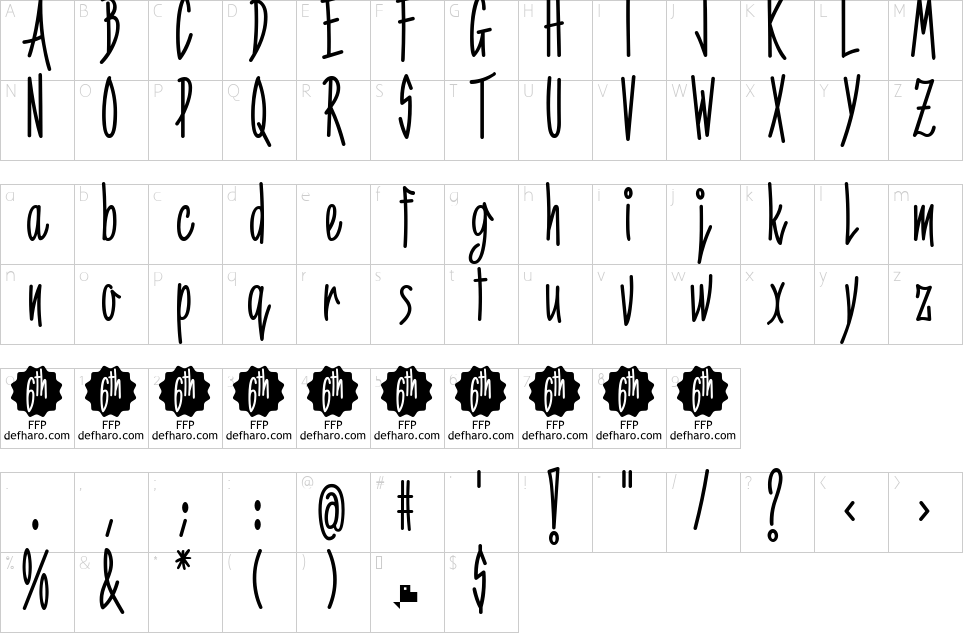
A fonte ‘6th Aniversario’ é uma criação estilosa que pode fazer um impacto significativo em seus projetos de design. Desenhada por deFharo, esta fonte foi desenvolvida com uma linguagem elegante e moderna, ideal para diversos estilos de design, como branding, propaganda ou design gráfico. Recentemente, a fonte foi baixada pelo número impressionante de 19,819 vezes, o que demonstra a sua popularidade e qualidade. Perfeita para usar em designs de escritório e em projetos de design de moda, ‘6th Aniversario’ é uma fonte versátil que vai desde gráficos simples até designs mais elaborados, oferecendo um acabamento cuidadosamente pensado que vai tornar sua proposta visual uma realidade. Descubra por si mesmo o poder de ‘6th Aniversario’ e adquira sua cópia hoje.